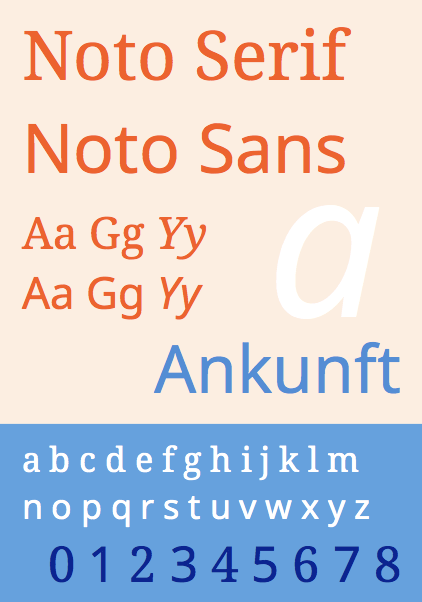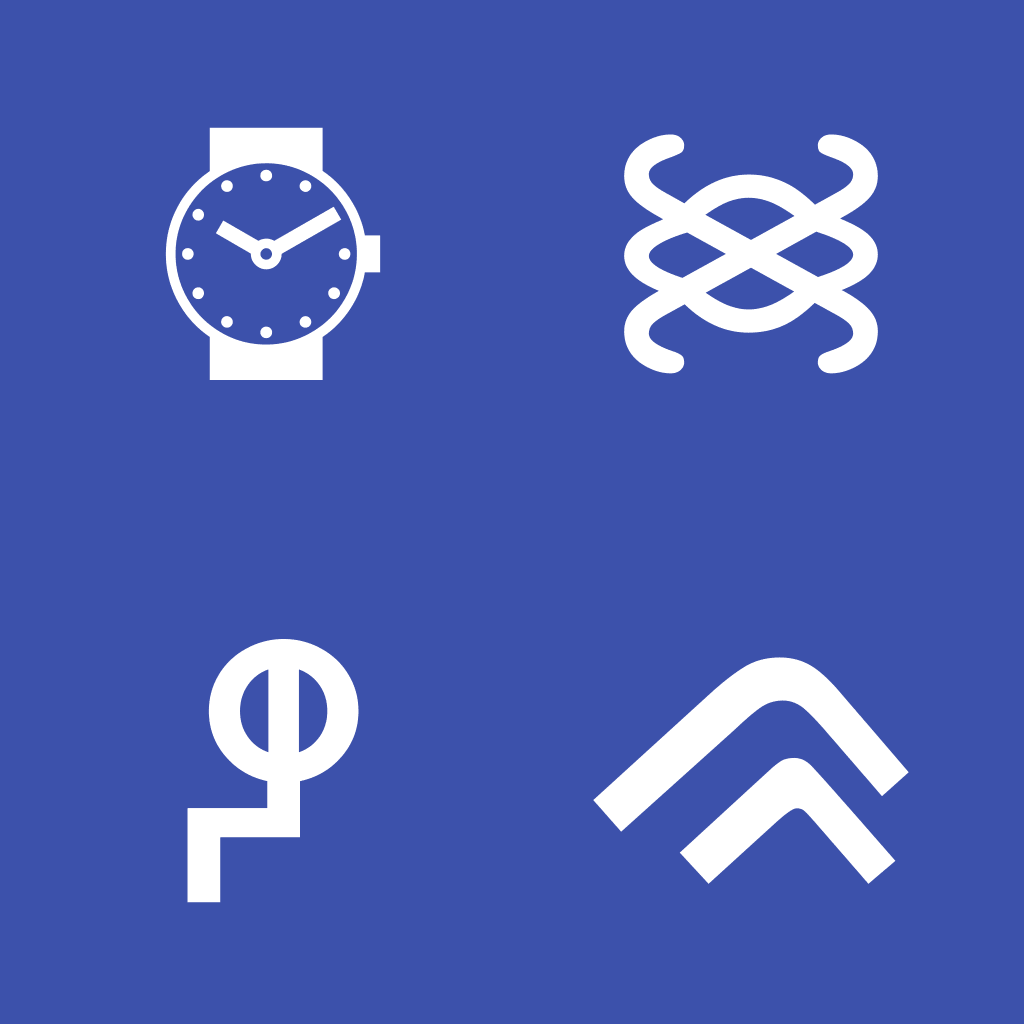
Tener un diseño fabuloso es fundamental. A veces, la elección de una fuente tipográfica puede llevarnos al éxito o fracaso en nuestras páginas web en función del público al que nos dirijamos. Para que nos evitemos un disgusto, Google Web Fonts ha lanzado Noto, una tipografía que quiere convertirse en la reina de las fuentes.
Esta tipografía de Google Web Fonts incluye 110.000 caracteres distintos y es compatible con más de 800 idiomas. Da igual si escribes en coreano, árabe, griego o español… ‘Noto Font’ te entenderá.
Elegir una tipografía no siempre es tarea fácil. ¿Quién no se ha roto la cabeza durante un buen rato intentando determinar cuál es la fuente ideal que más pegue con nuestro sitio web? Ya que, todos aspiramos a que nuestra página, que tantas lágrimas y sudor nos ha costado, consiga cosechar un elevado tráfico de visitas.
¿Eres fan de las tipografías y un usuario fiel de Google Web Fonts? Si estás leyendo este post lo más probable es que sí lo seas. Ya que, se han dignado a ponérnoslo fácil y han creado una tipografía universal que ha bautizado bajo el nombre de Noto. Se trata de una fuente que se convierte en su apuesta más fuerte de los últimos años y que quiere poner patas arriba el mundo del diseño web plantándole cara la actual líder de las tipografías: Helvetica.
El principal motivo por el que Google web fonts lanza ‘Noto’ es que la compañia tiene la necesidad de llevar a sus sistemas operativos Android y Chrome a todo el mundo. ¿Qué mejor forma de conseguirlo que eliminando las barreras de la comunicación que con una tipografía universal? Da igual si escribes en egipcio, griego, ruso o español; Noto se adaptará a tu idioma.
Noto es una tipografía Google web fonts de código abierto (sujeta a licencia Open Font License). Se ha desarrollado de la mano de otras grandes compañías del sector tales como Adobe, Monotype Imagin Inc y varios colaboradores expertos. Ellos han puesto gran esfuerzo para adaptar la fuente a idiomas tan complejos como el árabe o el hindú. Noto incluye aproximadamente 110.000 caracteres que le permiten operar en 800 lenguas diferentes para que podamos incluir en nuestra web. Además, prometen que mantendrán ‘Noto’ actualizada para ir introduciendo todos los nuevos caracteres que se vayan creando.
¿Qué es eso de tofu?
La palabra ‘Noto’ de Google deriva de ‘No more tofu’, no más tofu en español. Con ‘tofu’ no nos estamos queriendo referir a aquel manjar que tanto adoran los vegetarianos y algunos asiáticos. Esta palabra hace referencia a cuando nuestro ordenador nos muestra una caja en un texto de pantalla en lugar de una tipografía. Esto pasa cuando algún carácter en concreto no se puede mostrar por incompatibilidad con el mismo de la tipografía seleccionada. Esto es porque fonts como Times New Roman, Arial o similares no incluyen símbolos capaces de representarlo. Bien, pues Google web fonts ha encontrado la panacea para este problema visual que muchos diseñadores califican como feo.
Estas son algunas de sus características:
Por un lado ‘Noto Sans’ y ‘Noto Serif’, que contienen latín, griego y cirílico son un derivado de ‘Droids Fonts’. Ésta es una familia tipográfica diseñada por Steve Matteson para las pequeñas pantallas de móvil. Por otro lado, Noto Sans CJK es una tipografía desarrollada por Adobe y Google que contiene caracteres chinos, coreanos y japoneses. Además de letras del alfabeto latino y números tomado de la fuente ‘Source Sans Pro’. Y también está Noto Emoji Project’ que incluye emoticonos de colores en blanco y negro. La versión a color es usada por la interfaz web del Gmail y el navegador Chome.
“Cuando empezamos, nos dimos cuenta de lo enorme que era el reto. En árabe, por ejemplo, cada carácter tiene cuatro glifos (es decir, las formas que un carácter puede tomar) que cambian en función del texto que viene a continuación. En los idiomas hindúes, los glifos pueden reordenarse o incluso ser divididos en dos según el texto que los rodea”.
Google Web fonts nos quiere regalar la mayor apuesta tipográfica que tantos quebraderos de cabeza les ha costado. Porque sí, Noto Font se puede descargar de manera 100% gratuita. Siendo así, muy generosos por su parte. Ya que la Helvetica, si se descarga de manera oficial en su web, puede costar más de 800 dólares.
La descarga del pack completo que recopila absolutamente todas las variantes tipográficas de Noto pesa casi 500 megas. ¡Recuerda que son más de 800 idiomas con tipografías y glifos de elaboración compleja! No obstante; Google Web Fonts, el querido amigo de los diseñadores web, te permite descargar solo las que te interesen.
Ya disponible en Google Web Fonts:
Noto se suma al gran repertorio de fuentes tipográficas que nos ofrece Google Web Fonts, que ha renovado hace unas semanas el diseño de su página web. Ahora, en el momento de seleccionar las fuentes que queremos descargar nos permite visualizar un mapa de Google Maps. Éste nos señaliza con puntos rojos los países que utilizan la tipografía seleccionada. Nos echa una mano para que podamos visualizar qué países tienen más probabilidad de leer nuestro.